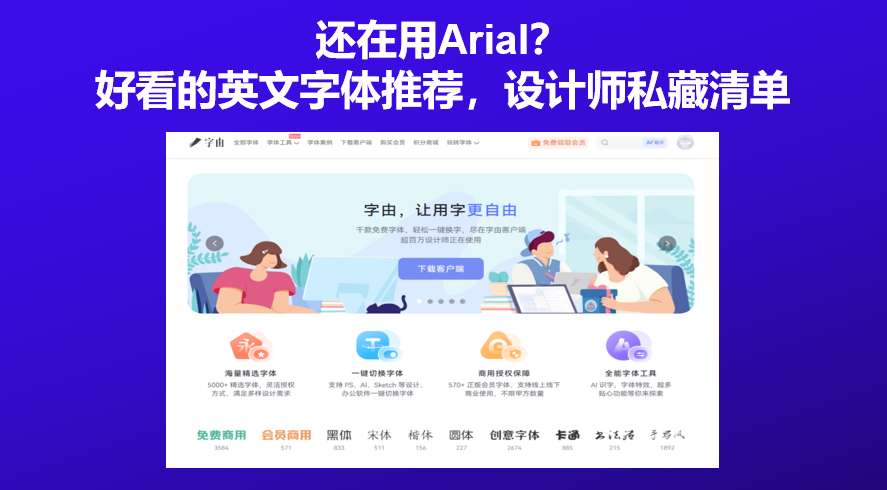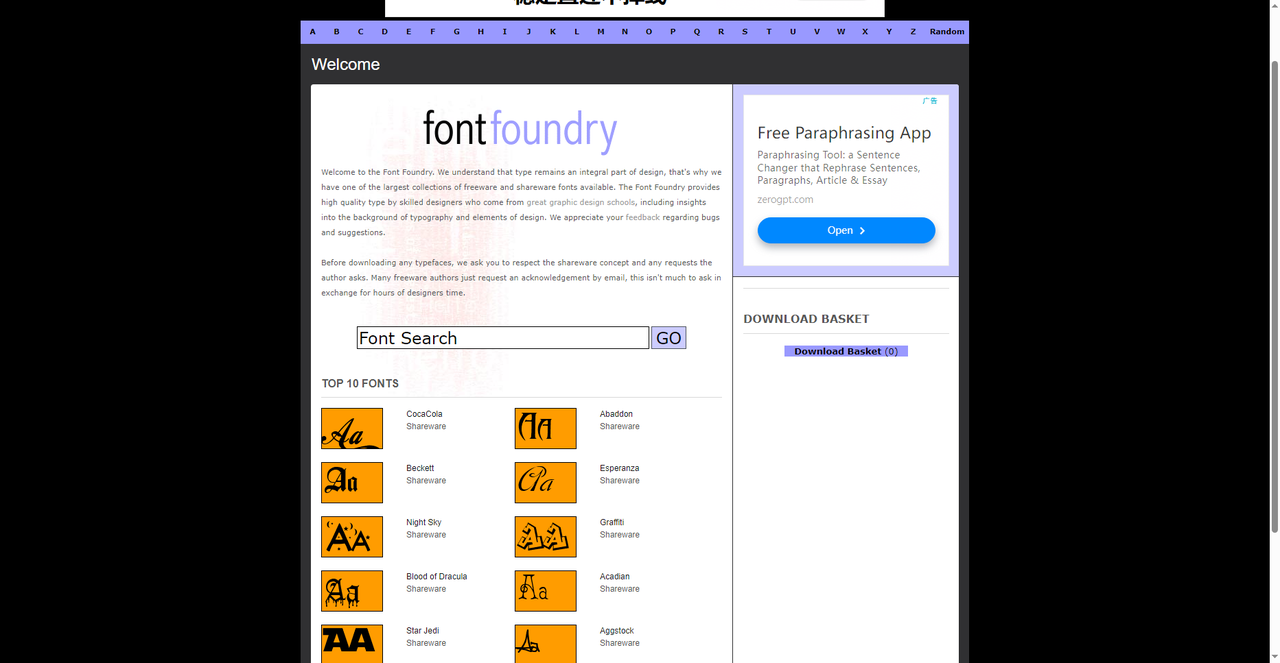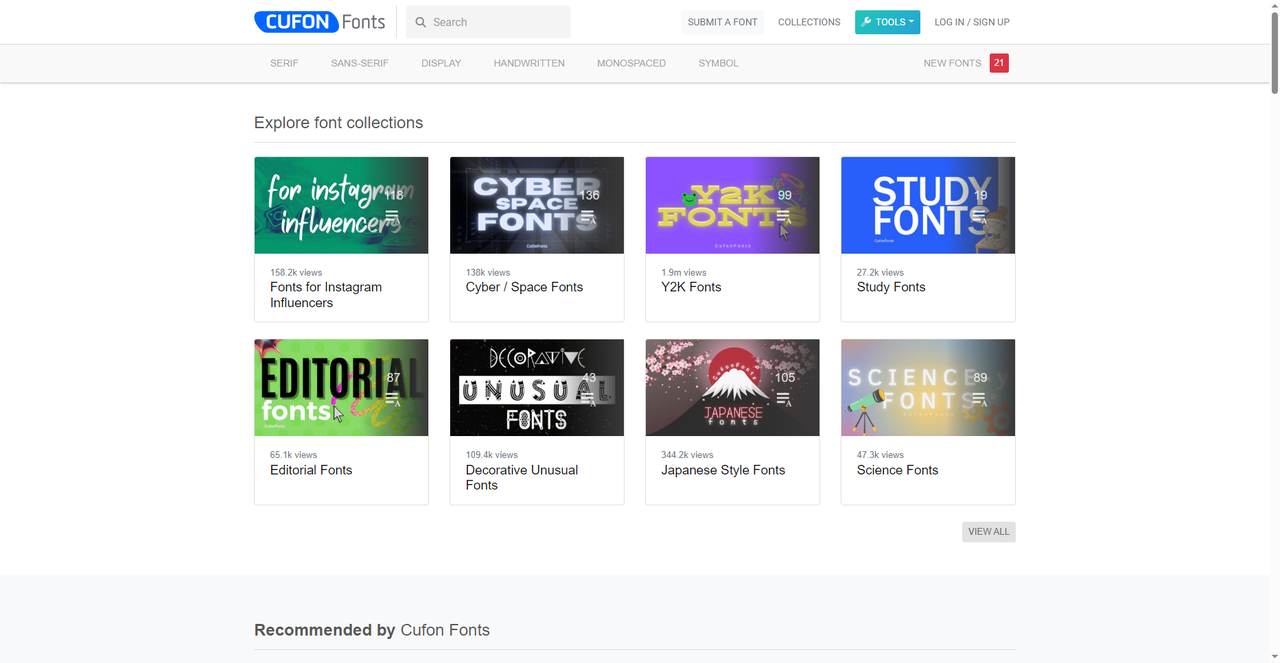
还在用Arial?好看的英文字体推荐,设计师私藏清单
如果你在做英文设计的时候还在PS里翻到 Arial、Times New Roman、Calibri 这几个最常见的字体的话,可千万不要再苦苦寻找了,不是不好用,是看久了真的会审美疲劳。想做一张有个性的英文海报,或者给品牌 Logo 找一款有辨识度的英文字体,默认字体库完全不够用。不过好消息是,互联网上有着很多高质量好看的英文字体资源,那么今天我就整理 5 个高质量的英文字体资源站,希望能帮到你。
先介绍一下字由,字由是目前国内设计师用得最多的字体管理与 AI 字体平台之一,注册用户超过 2000 万。字由收录了超过万款字体资源,涵盖中文、英文、日文、韩文等多语言字体。按用途分,品牌字体、正文字体、展示字体;按授权类型分,免费商用、设计师授权、订阅字体等等。
而且字由专门设置了免费商用字体专区,收录了阿里巴巴普惠体、腾讯字体、站酷系列字体、思源黑体等知名免费商用字体,每款字体都有清晰的授权说明。英文免费字体方面,字由有不少宝藏。比如 Loffers,一款极具个性的英文手写风字体,字形修长舒展,笔型融入独特斜切设计,笔画粗细均匀且偏粗,线条利落不拖沓。还有 BUBU-BOLD,粗字重设计兼具力量感与亲和力,适合标题设计、品牌视觉、科技主题海报,能快速抓住视觉焦点。Nunito Light 则是一款支持免费商用的多字重粗体字体,适用于品牌标识、海报设计、网页标题等多元场景,兼顾美观性与实用性。
字由还支持按语言、授权类型、风格分类快速筛选。选中“英文”,再选“免费商用”,所有可免费商用的英文字体一次性列出来。这种一站式的体验,确实比一个网站一个网站翻要方便太多。
2、Font Foundry
第二个网站是 Font Foundry。这是一个收录了大量免费和共享软件字体(shareware fonts)的网站,最大的特色是收录了很多模仿知名品牌的字体,比如可口可乐风格的字体、Abaddon 等哥特风格字体。如果你需要做复古风海报,或者想要一种带有品牌文化氛围的标题字,Font Foundry 是个不错的挖掘地。Font Foundry 首页展示了 CocaCola Shareware、Abaddon Shareware、Beckett、Esperanza、Night Sky 等热门字体,还提供了“下载篮”功能,可以批量选择多个字体包一次性打包下载。很多免费软件作者只要求使用后发一封邮件告知一声作为致谢,这种开放共享的氛围让 Font Foundry 收录的字体种类相当多样。
3、Cufon Fonts
第三个网站是 Cufon Fonts。Cufon 最早是一个用于网页字体渲染的 JavaScript 库,后来逐渐发展成了一个字体资源聚合平台。现在的 Cufon Fonts 是一个社区驱动的字体下载网站,字体由全球各地的设计师上传分享,风格覆盖面非常广。
Cufon Fonts 最有特色的地方是它的“集合”功能。比如“Instagram 网红字体”合集有 15.8 万次浏览量,“Y2K 字体”合集高达 190 万次浏览量,“日系风格字体”合集也有 34.4 万次浏览量。这些合集会按热度排序,能帮你快速找到当前流行什么风格的英文字体。在“推荐字体”区域,可以看到社区评分高的字体,比如 Vanilla Milk、Scarlett Mackenzie、Monstera Jam、Perandory 等。
4、FFONTS
这是全球最大的商业字体库之一,如果你需要购买一款正版英文字体的商业授权,这是目前最权威的平台之一,涵盖衬线体、无衬线体、手写体、展示体等各种分类。
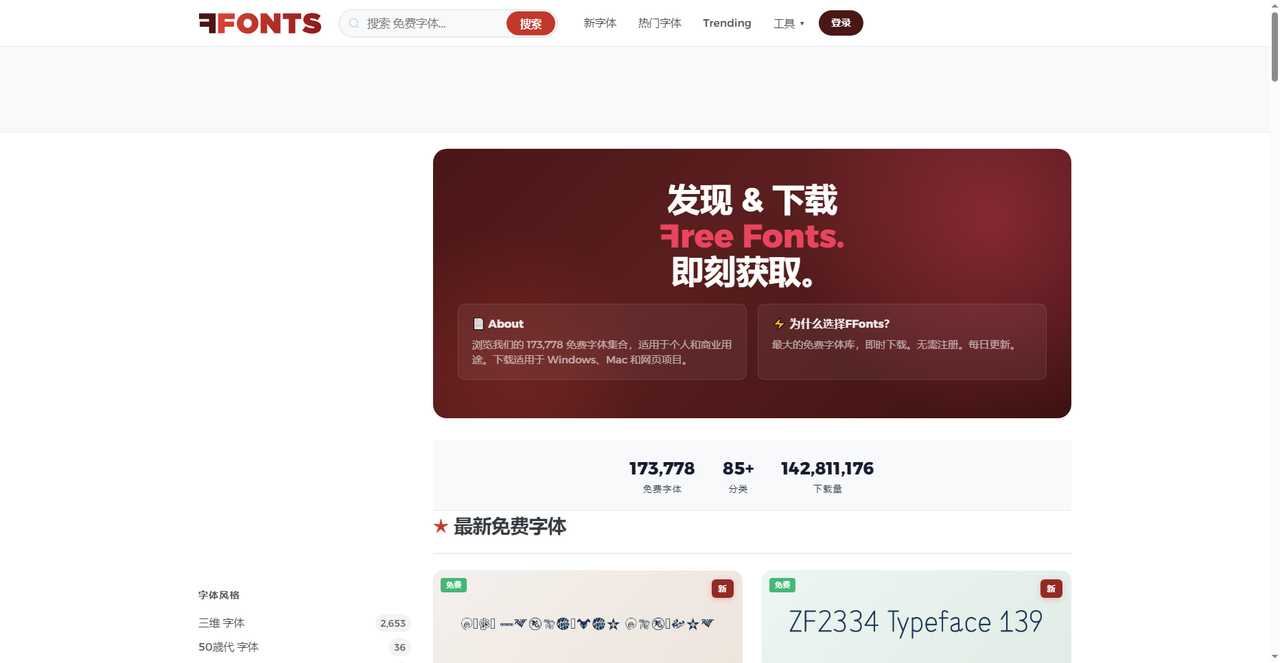
5、Fontsource
最后一个网站是 Fontsource。这是一个比较特别的字体网站,它不是给设计师下载字体文件的,而是给前端开发者用的——一个用于在网页应用中自托管开源字体的 NPM 包集合-。Fontsource 目前加载了 2077 个字体家族,包括 Inter、Roboto、Open Sans 等热门开源字体,同时支持可变字体(variable fonts),性能优化得不错。
普通设计师可能不需要接触 NPM 包,但 Fontsource 的“全家桶”思路值得了解一下:它把 Google Fonts 里所有开源字体都打包成了独立的 NPM 包,开发者可以直接通过 npm install 安装,然后在项目中按需加载。Fontsource 上的字体大多采用 SIL Open Font License v1.1 开源协议,个人和商业项目都可以免费使用-。如果你平时做网页设计,或者需要把字体嵌入到数字产品中,Fontsource 是 Google Fonts 之外一个高质量的开源替代方案。它的优势是字体可以自托管,不依赖外部 CDN,加载速度和隐私控制都更好。
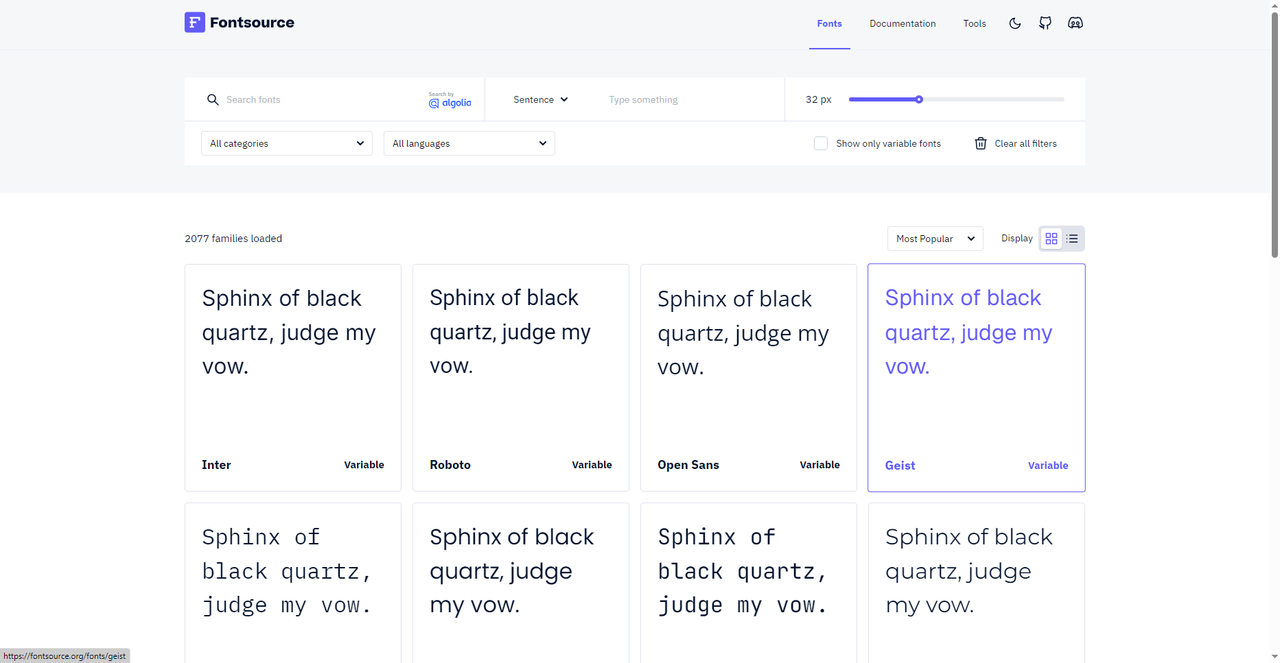
以上就是今天介绍的5 款好看的英文字体网站推荐,字由最适合国内设计师,2 万多款字体加一键激活功能,从找字体到用字体全流程不用切换软件,免费商用字体专区授权清晰;Font Foundry 适合复古风格和品牌仿制字体的爱好者,能翻到很多别处找不到的有趣字体;Cufon Fonts 社区氛围浓厚,Y2K、Instagram 网红字体这些流行合集能帮你快速捕捉设计趋势,可以根据自己的兴趣方向来选择!